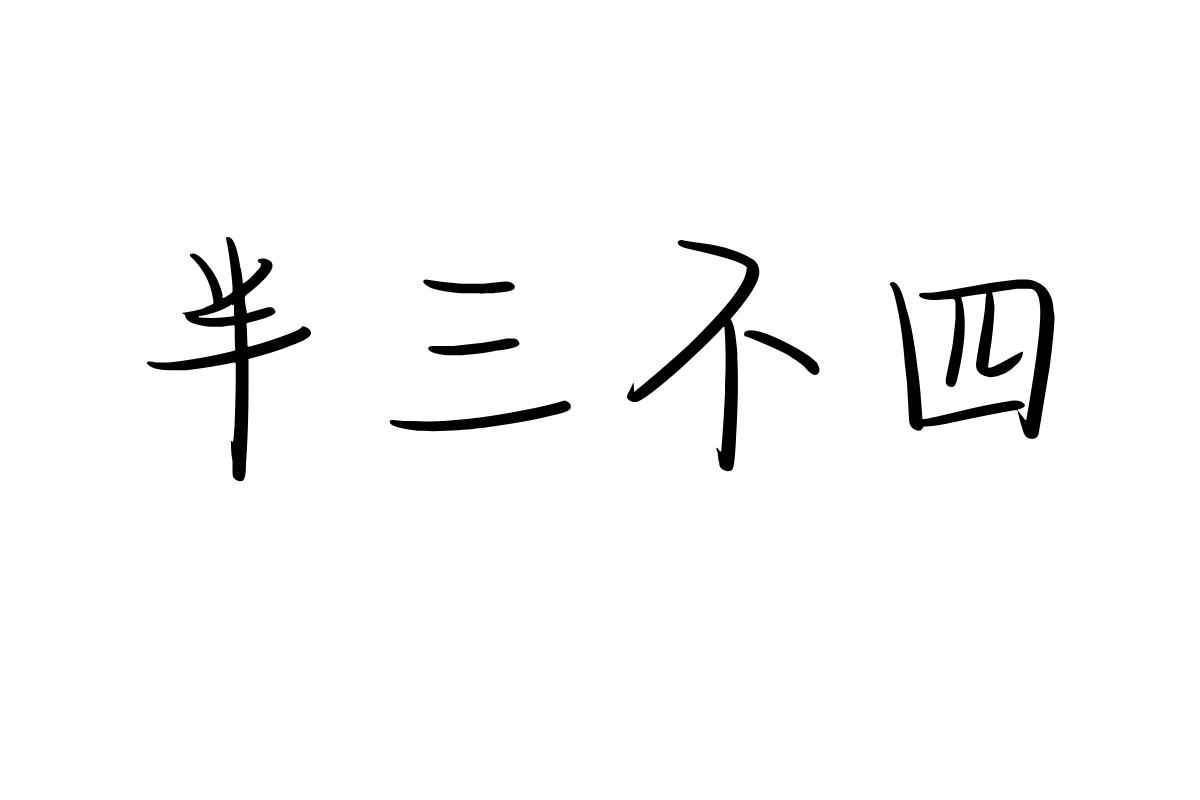
也字工厂雨眠手迹是一款具有独特韵味和艺术感的字体。这款字体采用了独特的手写风格,笔画流畅自然,线条粗细不一,给人一种别具一格的感觉。它的字形结构紧凑,但又能保持一定的空间,使得整体看起来既紧凑又不失美感。
在设计上也颇具匠心,每个字都经过精心设计,力求达到最佳的视觉效果。无论是用于标题、正文还是装饰性文字,都能让你的作品焕发出不一样的风采。
总的来说,也字工厂雨眠手迹是一款非常适合用于个性化创作和设计的优秀字体。无论你是设计师、艺术家还是普通用户,都能从这款字体中找到属于自己的独特魅力。